01 钟齐马善政毛笔楷书
特点:毛笔楷书
02 字体视界法棍体
特点:标准化(采用 GB2313 编码,收容 7608 个字符)、多样化(笔画纤细,规律加粗,曲线折角)、场景化(适合用于不同场景)
03 字体视界法棍体拼音版
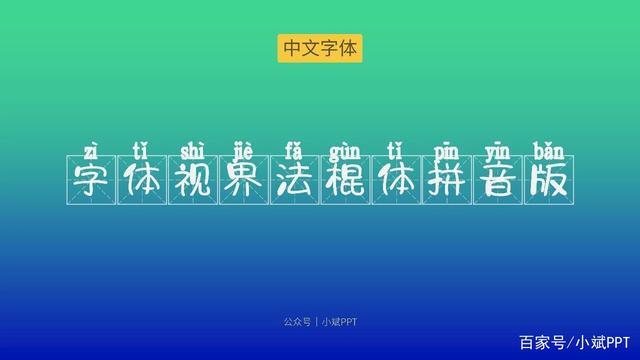
特点:拼音体,字体视界法棍体的拼音版
04 江西拙楷体
特点:手写楷体
05 Cascadia Code
特点:微软于 2019 年微软开发者大会发布,设计自 Aaron Bell,等宽字型,适于终端机和文本编辑器,编程连字